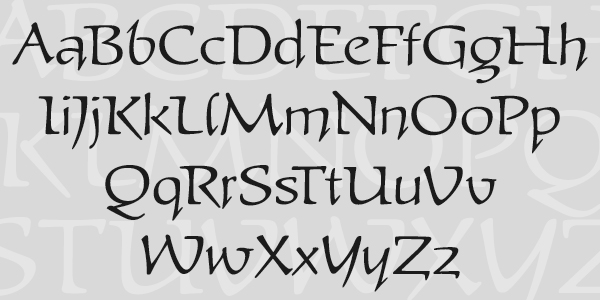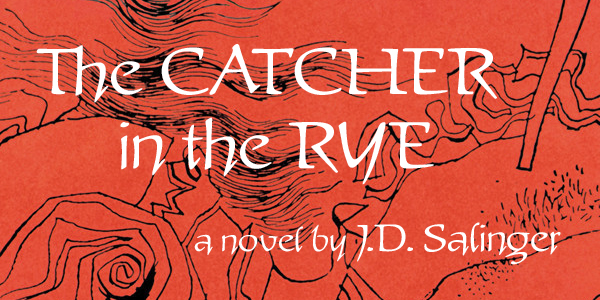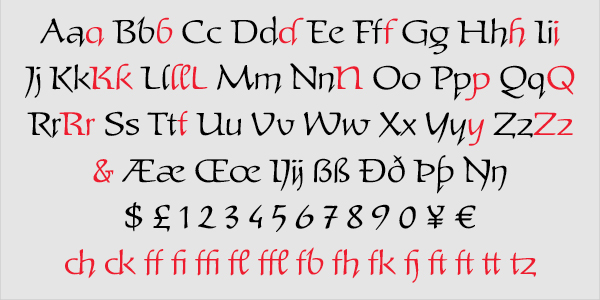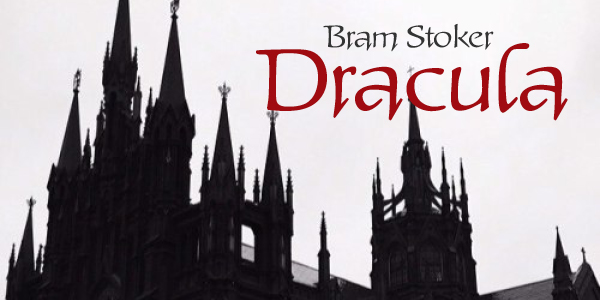
P22 veröffentlichte 2017 mit der Schumann Pro eine bislang unveröffentlichte Arbeit des aus Chemnitz stammenden Kalligrafen Heinz Schumann. Diese Schrift war ein Projekt des Schülers von Albert Kapr und Herbert Thannhaeuser während seiner Zeit an der Hochschule für Grafik und Buchkunst Leipzig.
Digitalisierung und Ausbau der Schumann Pro erfolgten durch Patrick Griffin und Richard Kegler. Die Schrift besteht aus einem Schnitt mit über 500 Glyphen.